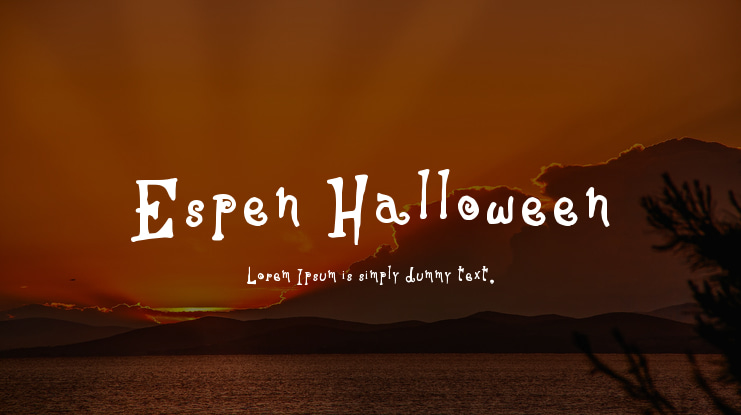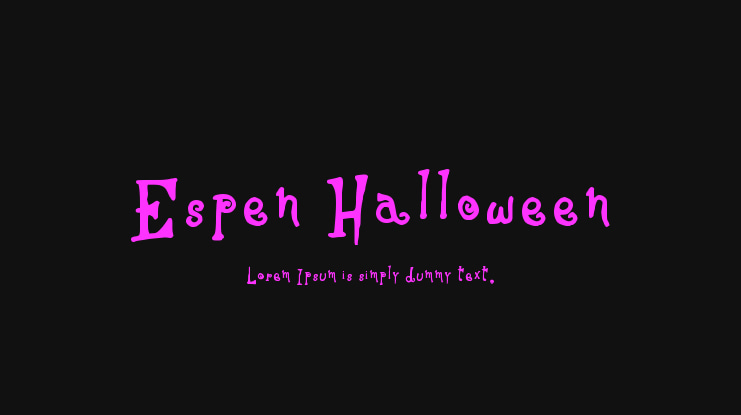
Espen Halloween Font
Dopo le font ESPEN-COMICS visto la richiesta e l'esigenza di fare qualcosa per HALLOWEEN, ho disegnato la nuova FONT ESPEN-HALLOWEEN, così anche in questa stupenda ricorrenza abbiamo una font adeguata per fumentti ed altro utilizzo libero!